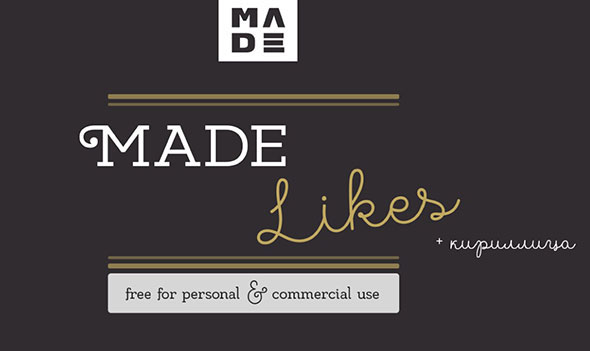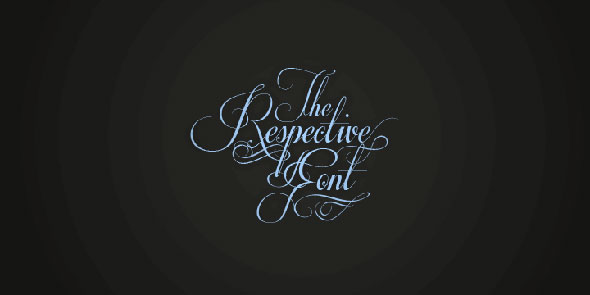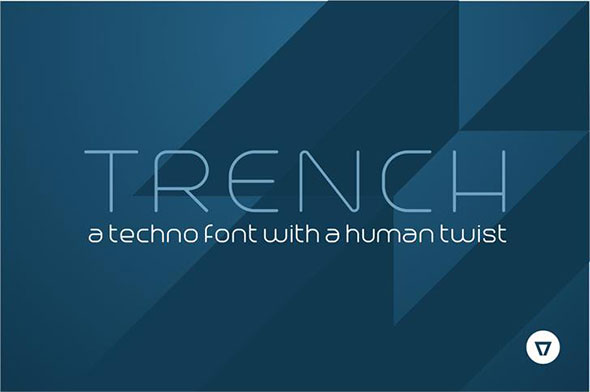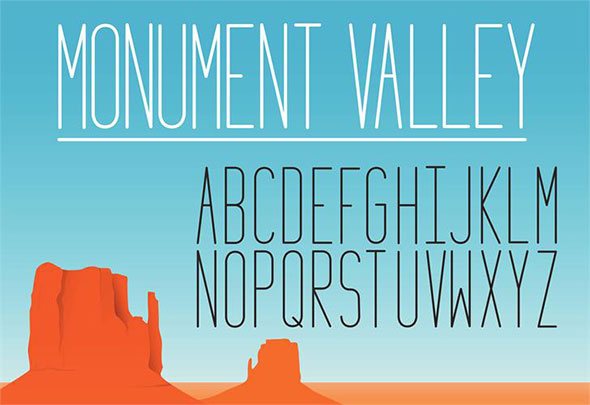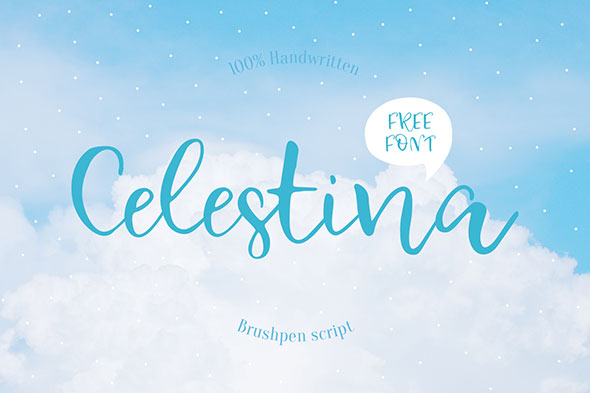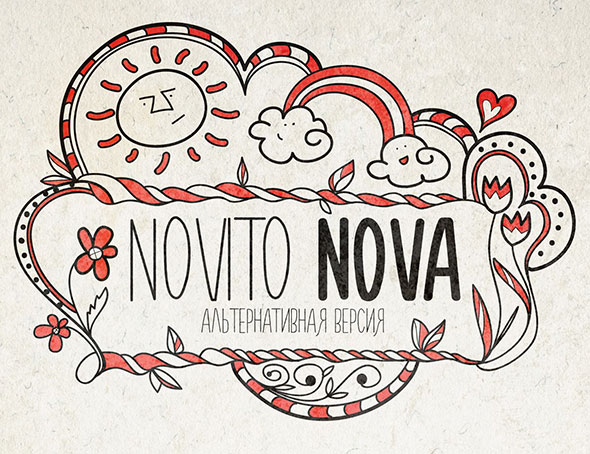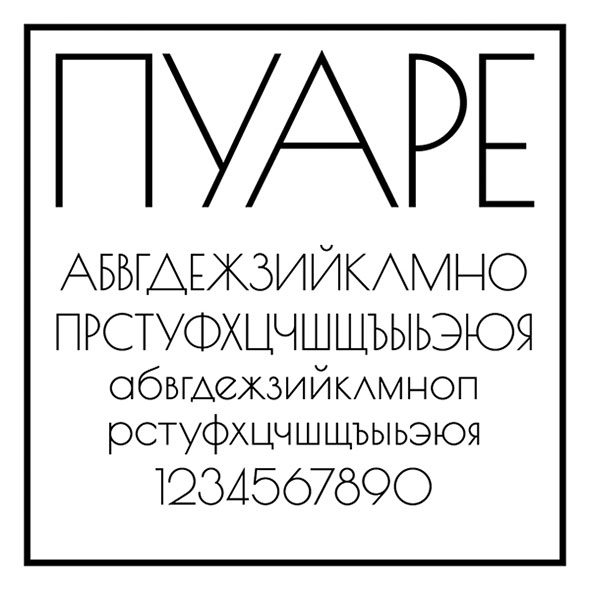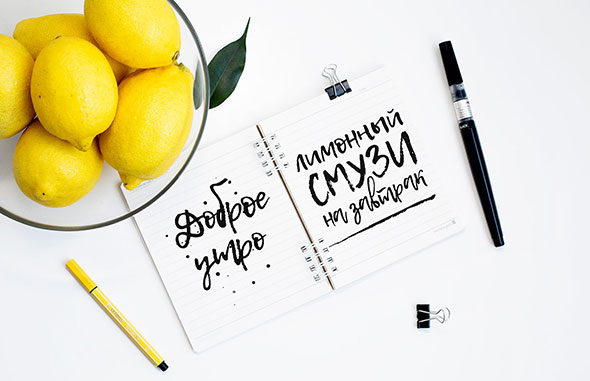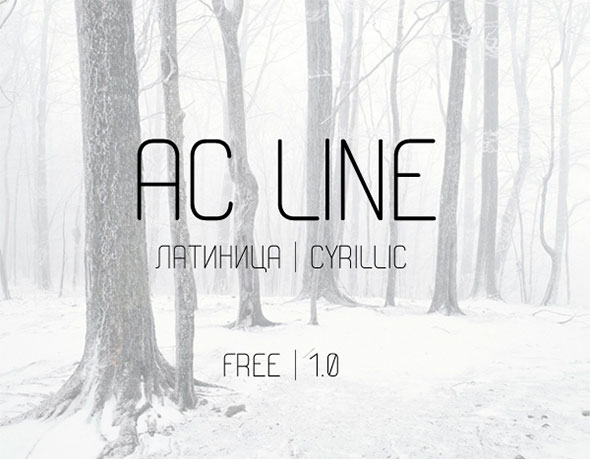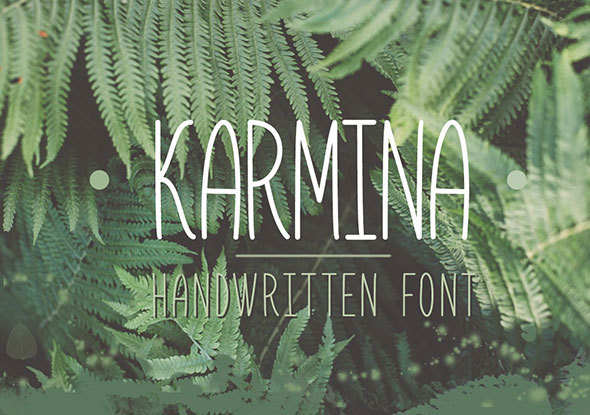
Бесплатные тонкие шрифты для элегантного дизайна
Ничто не подчеркивает элегантность дизайна как красивый, утонченный шрифт. Типографика оказывает сильнейшее влияние на настроение и стиль всей композиции. Сегодня мы собрали бесплатные тонкие шрифты, которые помогут вам в работе. Первая часть подборки состоит из начертаний, в которых присутствует и кириллическая версия. Пожалуйста будьте внимательны к условиям использования! Некоторые шрифты бесплатны только для личного пользования.
Кириллица
MADE LIKES
Celestina
Novito NOVA
POIRET
Lemon Tuesday
AC Line
Karmina
Arcadia
Латиница
Riverside Avenue
Respective
Trench
Before the Rain
Honeymoon
Canela Bark
Monument_Valley_1.2